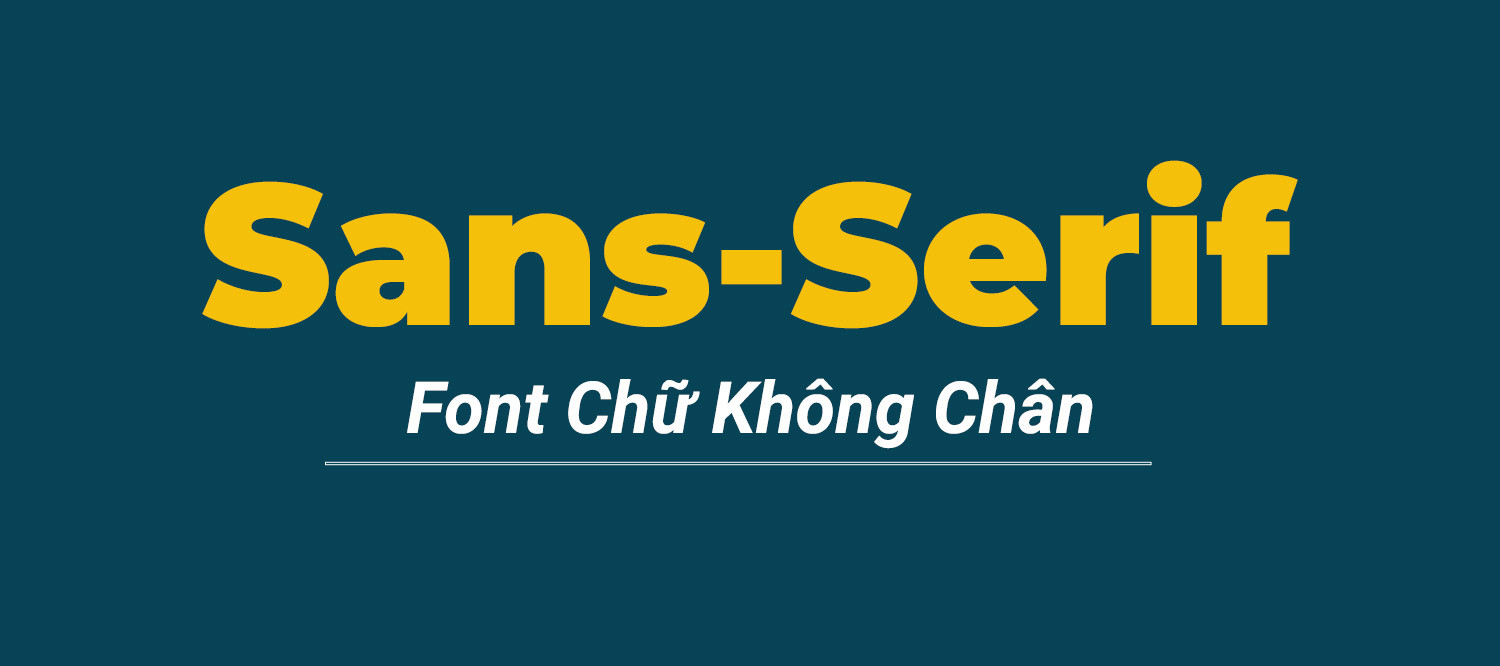
Font chữ không chân, hay còn gọi là sans-serif, là một loại font chữ mà các ký tự không có các đường nét ngang nhỏ ở đầu hoặc cuối các nét chính. Đặc điểm này làm cho font chữ không chân trở nên đơn giản, hiện đại và dễ đọc hơn trong nhiều trường hợp.
Font chữ không chân thường được sử dụng rộng rãi trong các thiết kế hiện đại, từ giao diện web, ứng dụng di động, đến các tài liệu in ấn như tờ rơi, biển quảng cáo, và báo chí. Một số font chữ không chân phổ biến bao gồm Arial, Helvetica, và Calibri.
Ưu điểm lớn nhất của font chữ không chân là tính dễ đọc, đặc biệt trên các màn hình kỹ thuật số. Các ký tự rõ ràng, không có chi tiết thừa giúp mắt người đọc không bị mỏi khi đọc trong thời gian dài. Ngoài ra, font chữ không chân cũng mang lại cảm giác gọn gàng, hiện đại và chuyên nghiệp, phù hợp với các thiết kế mang tính chất công nghệ, kinh doanh, và truyền thông.
Font chữ không chân (sans-serif) luôn là lựa chọn ưu tiên cho các thiết kế hiện đại nhờ tính đơn giản, dễ đọc và tính thẩm mỹ cao. Dưới đây là 10 font chữ không chân đẹp và phổ biến, được các nhà thiết kế ưa chuộng:
SVN Alfreda: Một trong những font chữ không chân nổi tiếng và được sử dụng rộng rãi nhất. Helvetica nổi bật với các đường nét rõ ràng, cân đối và dễ đọc.
Arial: Arial là một font chữ không chân phổ biến, được biết đến với thiết kế đơn giản, dễ đọc và linh hoạt. Với các đường nét rõ ràng và sạch sẽ, Arial thích hợp cho nhiều ứng dụng, từ tài liệu văn phòng, trang web đến thiết kế đồ họa. Sự dễ đọc và tính đa dụng của Arial khiến nó trở thành một lựa chọn ưa thích trong nhiều dự án thiết kế và trình bày văn bản. Font chữ này không chỉ mang lại sự chuyên nghiệp mà còn giúp tối ưu hóa trải nghiệm người dùng trên các nền tảng kỹ thuật số.
Roboto: Font chữ này được Google phát triển, thường được sử dụng trong các ứng dụng Android và giao diện người dùng của Google. Roboto mang phong cách hiện đại và thân thiện.
TH Rukino: Là một font chữ hiện đại, dễ đọc và rất linh hoạt, font chữ cứng cáp mang cảm giác mạnh mẽ cho người xem, dùng cho các dự án sản phẩm liên quan để thể thao, giải trí, sức mạnh…
Beuau Sans: Với thiết kế tinh tế và thanh lịch,mang đến cảm giác chuyên nghiệp và trang nhã, phù hợp cho các dự án từ in ấn đến kỹ thuật số.
Montserrat: Font chữ này nổi bật với các đường nét đậm và cân đối, tạo nên phong cách hiện đại và mạnh mẽ, thường được sử dụng trong thiết kế logo và tiêu đề.
TH Tokyo: Là một font chữ không chân cổ điển, TH Tokyo có thiết kế gọn gàng, đơn giản nhưng rất mạnh mẽ và dễ nhận diện.
TH Rasnico: Kết hợp giữa các yếu tố của cả Arial và Helvetica, font chữ mang cảm giác hiện đại và sang trọng. Là một font chữ rất phổ biến trong thiết kế web và in ấn.
Be Vietnam Pro: Được kế thừa từ Be Vietnam (2019), bộ phông chữ Be Vietnam Pro do tác giả Lâm Bảo phát triển đã chính thức có mặt trên Google Fonts, kèm theo nhiều cải tiến về mẫu chữ trong tiếng Việt, khả năng thích ứng với dấu phụ và phong cách thiết kế gọn gàng, dễ đọc nhất. Phù hợp để sử dụng dùng cho các công ty công nghệ và startup. Với các đường nét mềm mại và cân đối, Be Vietnam Pro mang đến sự cân bằng hoàn hảo giữa tính hiện đại và cổ điển, phù hợp cho nhiều loại dự án.
Gotham: Nổi tiếng với thiết kế đơn giản nhưng đầy mạnh mẽ, Gotham thường được sử dụng trong thiết kế logo, tiêu đề và các biển quảng cáo.
Mỗi font chữ không chân đều mang những đặc trưng riêng, giúp các nhà thiết kế có thể lựa chọn và kết hợp linh hoạt để tạo nên những sản phẩm thiết kế ấn tượng và chuyên nghiệp.
Tuy nhiên, font chữ không chân cũng có thể thiếu đi sự mềm mại và cổ điển mà các font chữ có chân (serif) mang lại. Do đó, việc lựa chọn giữa font chữ có chân và không chân cần dựa vào mục đích sử dụng và phong cách thiết kế tổng thể. Trong thiết kế đồ họa, sự kết hợp hài hòa giữa hai loại font chữ này có thể tạo nên những sản phẩm độc đáo và ấn tượng.